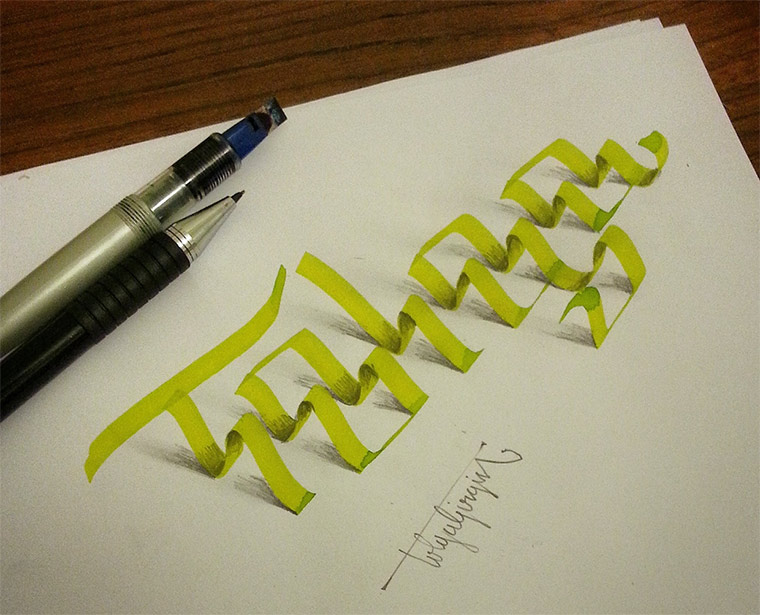
Schattierungen gekonnt gesetzt
3D-Typografie: Tolga Girgin
3D-Typografie: Tolga Girgin Tolga_Girgin_01
Zu Jahresbeginn hatte ich die gekonnt mit 3D-Effekt gezeichneten Typografie-Motive von Lex Wilson hier. Die Arbeiten des türkischen Grafik-Designers Tolga Girgin gehen in eine ganz ähnliche Richtung. Leider verhunzt der die Fotos seiner gekonnt schattierten Zeichnungen mit irgendwelchen Fotofiltern (oder belichtet sie einfach schlecht), so dass die Ergebnisse teils etwas schrummelig ausschauen. Und ja, das ist ein Wort. Ab jetzt zumindest… Dennoch sehr kurzweilig anzuschauen, da ist aber sicherlich noch mehr möglich. Saubereres Ausarbeiten würde den Effekt nochmals intensivieren, so schaut das teils wie Kritzeleien auf der Hörsaalbank oder während des Telefonierens aus.
3D-Typografie: Tolga Girgin Tolga_Girgin_02
3D-Typografie: Tolga Girgin Tolga_Girgin_03
3D-Typografie: Tolga Girgin Tolga_Girgin_04
3D-Typografie: Tolga Girgin Tolga_Girgin_05
3D-Typografie: Tolga Girgin Tolga_Girgin_06
3D-Typografie: Tolga Girgin Tolga_Girgin_07
3D-Typografie: Tolga Girgin Tolga_Girgin_08